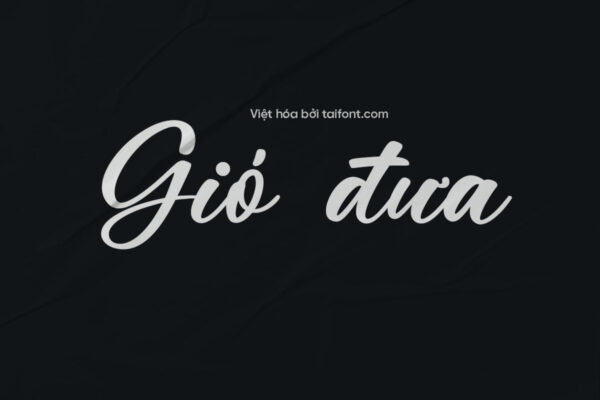
Font Việt hóa TF Kactigona là một font chữ viết tay có nét đậm, được thiết kế bởi các chuyên gia để mang lại nét độc đáo cho các thiết kế về đám cưới. Với Font Việt hóa TF Kactigona, bạn có thể tạo ra những thiết kế ấn tượng và thu hút.
Ứng dụng của Font Việt hóa TF Kactigona
Font Việt hóa TF Kactigona có thể được sử dụng trong nhiều lĩnh vực khác nhau, bao gồm thiết kế đám cưới, thiết kế đồ họa, thiết kế web…
Ưu điểm của Font Việt hóa TF Kactigona
Đặc điểm nổi bật
Font Việt hóa TF Kactigona có nét đậm, rõ ràng, dễ đọc và dễ sử dụng.
Sự linh hoạt
Font Việt hóa TF Kactigona có thể được sử dụng trong nhiều phong cách thiết kế khác nhau, từ hiện đại đến cổ điển.
Ví dụ về Font Việt hóa TF Kactigona
Dưới đây là một số ví dụ về cách sử dụng Font Việt hóa TF Kactigona trong thiết kế đám cưới:
- Sử dụng Font Việt hóa TF Kactigona cho tiêu đềinvitation đám cưới.
- Sử dụng Font Việt hóa TF Kactigona cho tiêu đề menu đám cưới.
Lợi ích của việc sử dụng Font Việt hóa TF Kactigona
Sử dụng Font Việt hóa TF Kactigona mang lại nhiều lợi ích cho thiết kế đám cưới của bạn, bao gồm:
- Tạo ra nét độc đáo và ấn tượng.
- Có thể được sử dụng trong nhiều lĩnh vực khác nhau.
Font Việt hóa TF Kactigona là một lựa chọn độc đáo cho thiết kế đám cưới của bạn. Hãy thử sử dụng Font Việt hóa TF Kactigona ngay hôm nay và tạo ra những thiết kế ấn tượng!
Font Việt hóa TF Kactigona